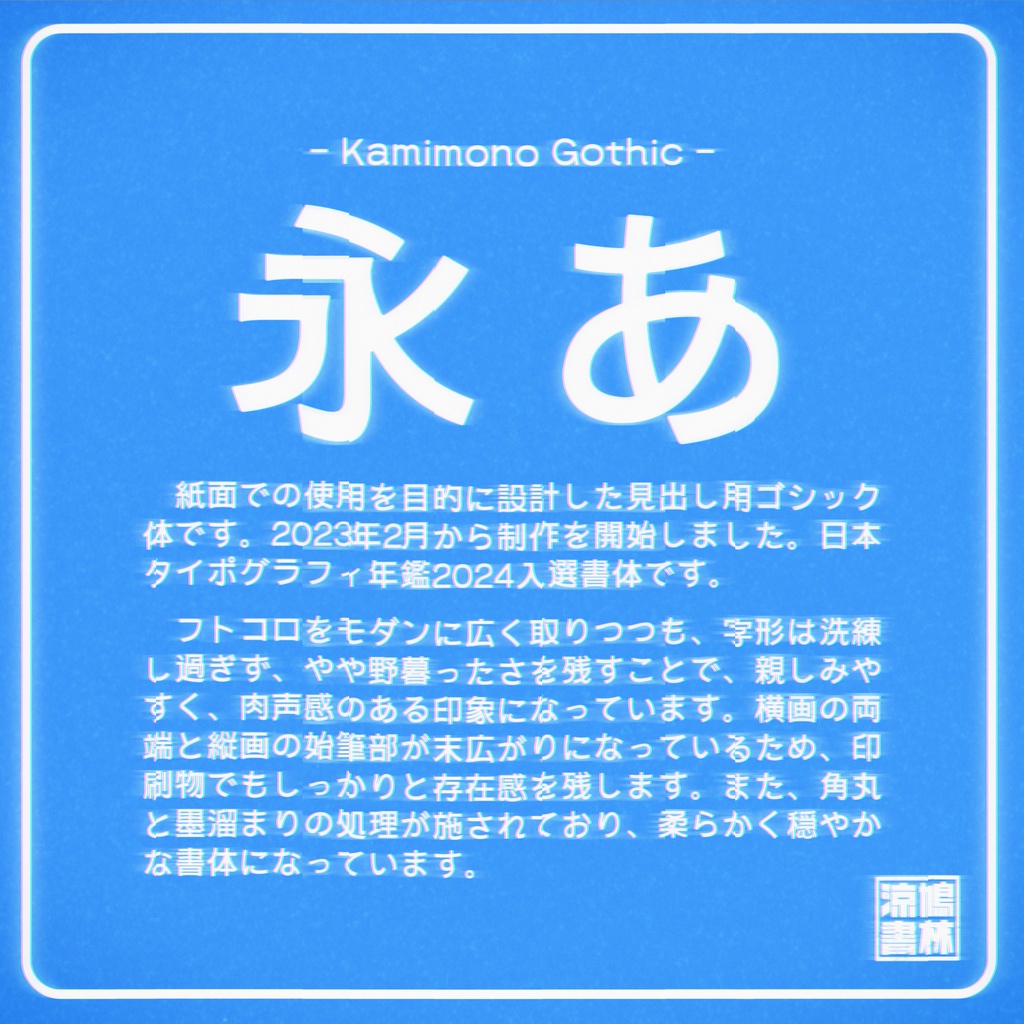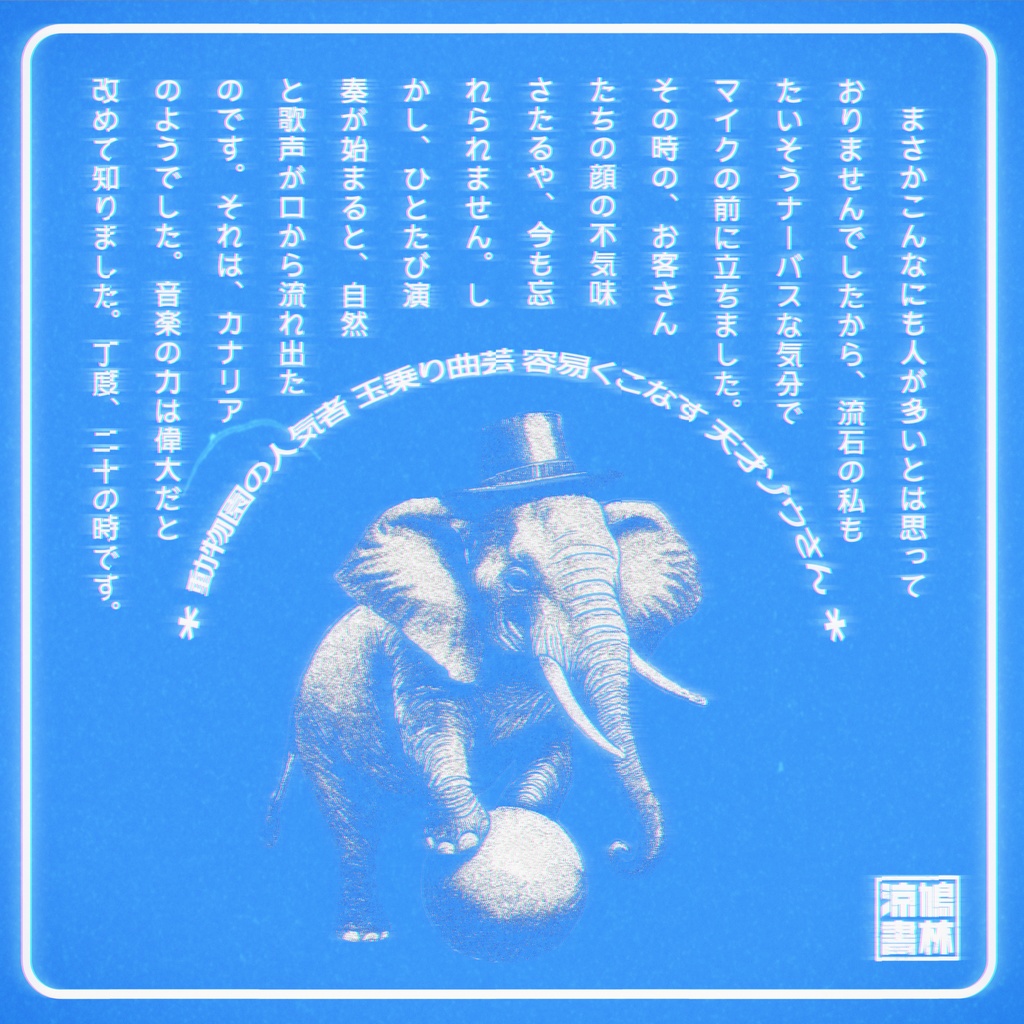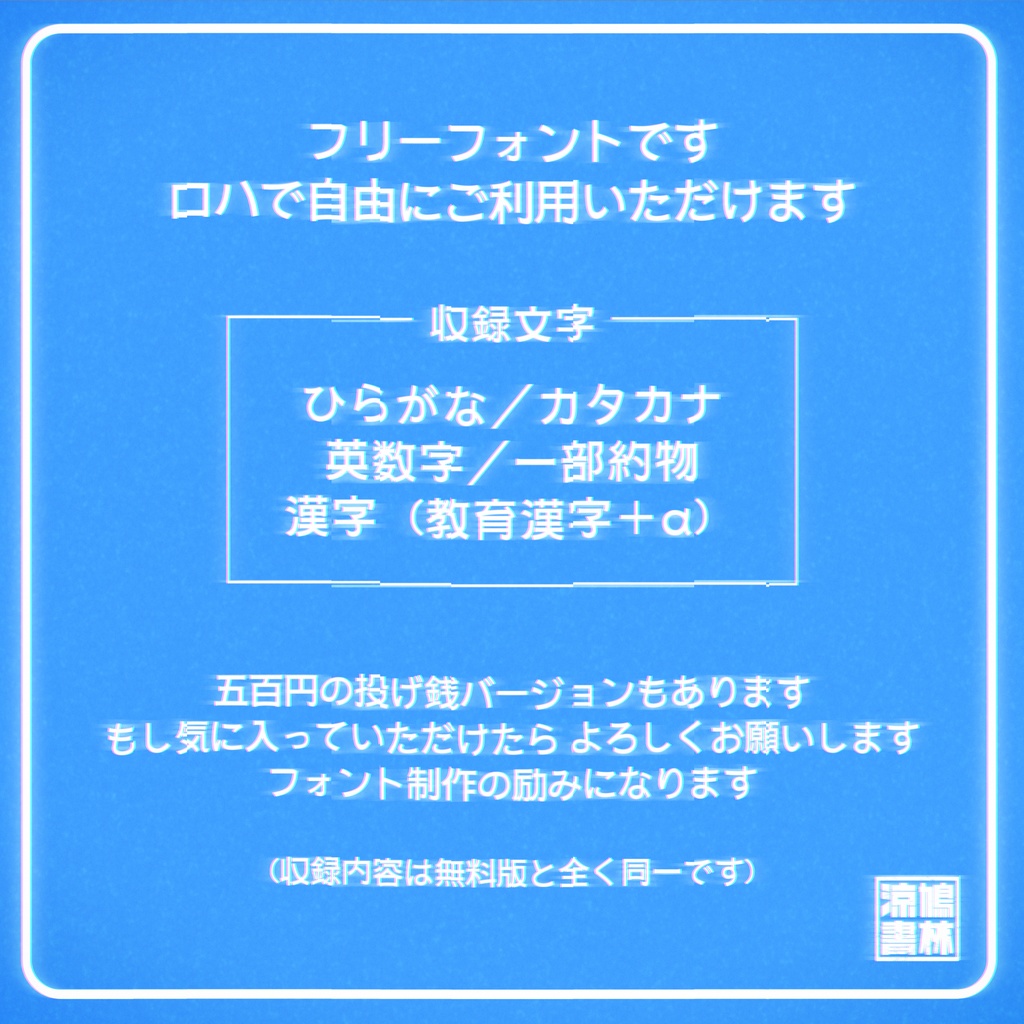
【フリーフォント】紙モノゴシック
【このフォントについて】 紙面での使用を目的に設計した見出し用ゴシック体です。 フトコロをモダンに広く取りつつも、字形は洗練し過ぎず、やや野暮ったさを残すことで、親しみやすく、肉声感のある印象になっています。横画の両端と縦画の始筆部が末広がりになっているため、印刷物でもしっかりと存在感を残します。また、角丸と墨溜まりの処理が施されており、柔らかく穏やかな書体になっています。 ※投げ銭版の収録内容は無料版と全く同じです。もし気に入っていただけたらよろしくお願いします。フォント制作の励みになります。 無償利用・商用利用問わず、自由にご使用いただけます。 印刷物のみならず、ゲームやWebなど何にでもご活用ください。 当フォントを利用した制作物などを、X(旧Twitter)で報告していただけると、とても励みになります。 不具合の修正や新しいグリフの追加が行われていますので、最新のバージョンをご確認ください。 【すずみばと書林】 《もじピジョン》と《Suzumi Designs》による2人組のフォント制作ユニットです。 共同制作のフォントを配布・販売しています。 「書林」は本来「多くの書籍が集まるところ」という意味ですが、ここでは「多くの書体が集まるところ」という意味を込めて名付けました。 新作フォントの公開やバージョンの更新情報はそれぞれのX(旧Twitter)でアナウンスしています。当フォントダウンロードの折には、フォローしていただけると幸いです。 《もじピジョン/X(旧Twitter)》https://twitter.com/Moji_Pigeon 《Suzumi Designs/X(旧Twitter)》https://twitter.com/Suzumi_Designs 【収録文字】 ひらがな・カタカナ・英数字・一部約物・漢字(教育漢字+α) (最新ver.2.1) 【更新履歴】 ver.1.1 リリース ver.1.2 不具合の修正 ver.2.1 グリフの新規追加・修正など 【利用規約】 ・利用条件 1)当フォントを入手・使用したことによるいかなる損害も使用者自身が責任を負うものとします。 2)無償利用・商用利用ともにご自由にお使いいただけます。 3)クレジットの表記は不要です。 4)当フォントの二次配布は可能ですが、その際はこのtxtファイルを添付するようにしてください。なお、二次配布の際は一言いただけると幸いです。 5)当フォントを加工・変形してご利用いただけます。 6)ゲームやWebサイトに埋め込んでご利用いただけます。 ・禁止事項 1)当フォントを公序良俗に反する目的で使用することはできません。 2)当フォントを利用したロゴマーク等の商標登録はできません。 3)当フォントデータ・プログラムを、無断で改変したものを配布することはできません。 4)当フォントの制作者を騙った発言等はできません。